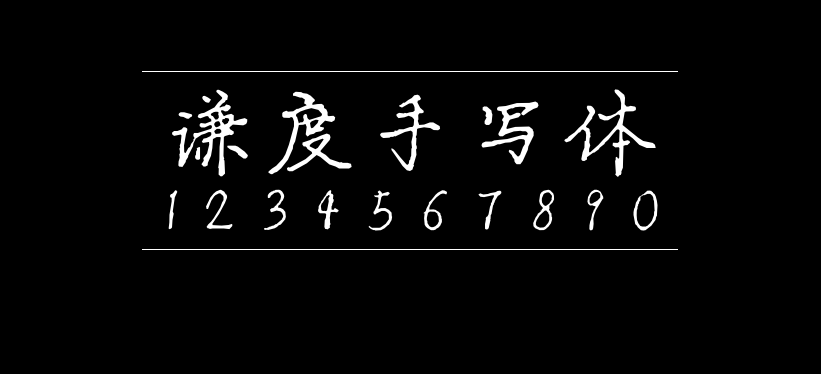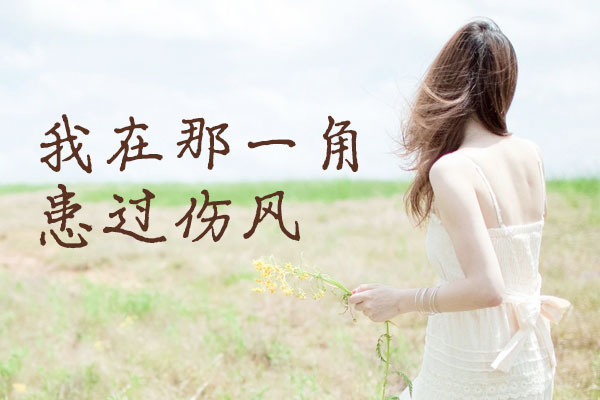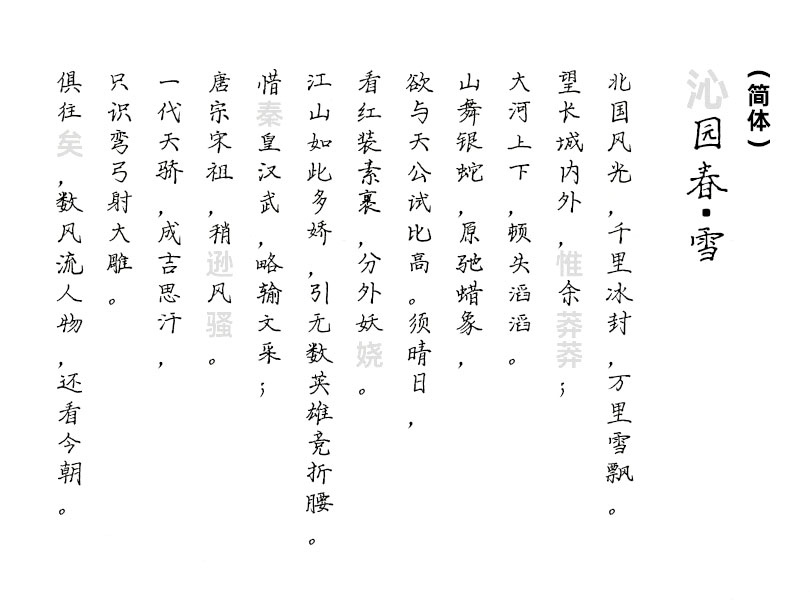
字体下载 谦度手写楷体
谦度手写楷体
谦度手写楷体(qiando手写楷体)是B站的UP主只有三岁的谦度QIANDO自己手写制作的一款字体。 这套字体用的时间说长不长说短不短,花费很多心思,一笔一画写了5000多个字写出来的。
谦度手写楷体是一款十分接地气的手写字体,字体就跟我们平时用圆珠笔写出来的一样。而字体写得也比较漂亮,干净整洁,值得推荐。而UP主也十分善心,将这套字体免费商用!
需要注意的是,该字体目前有五千多字,有部分字符是不全的。